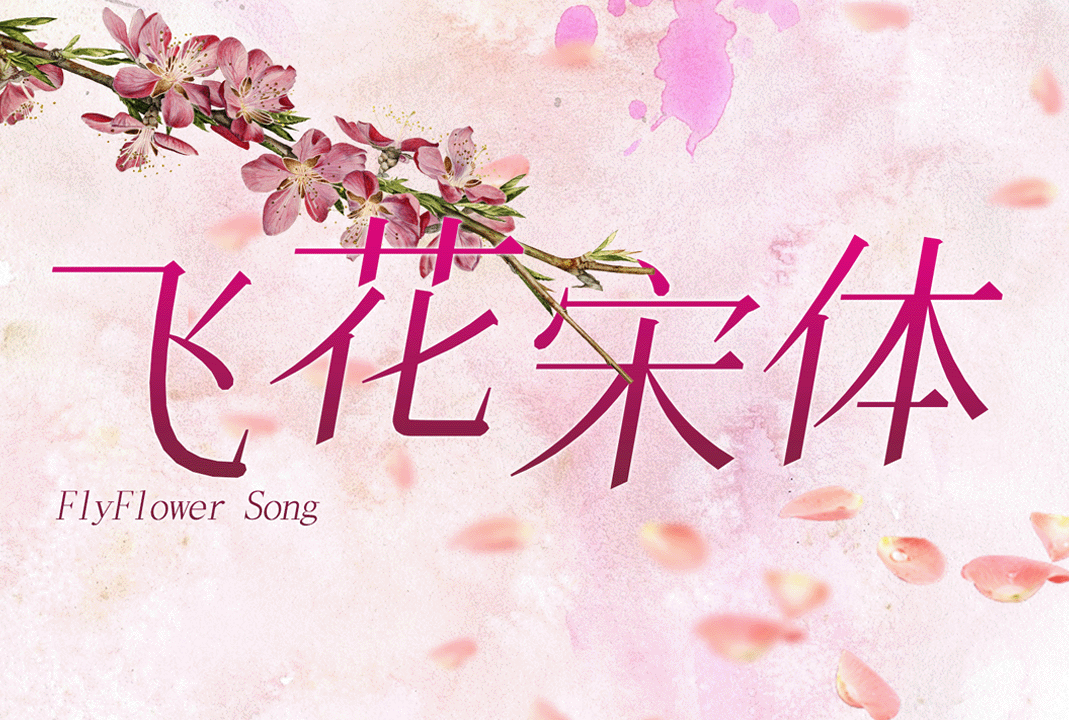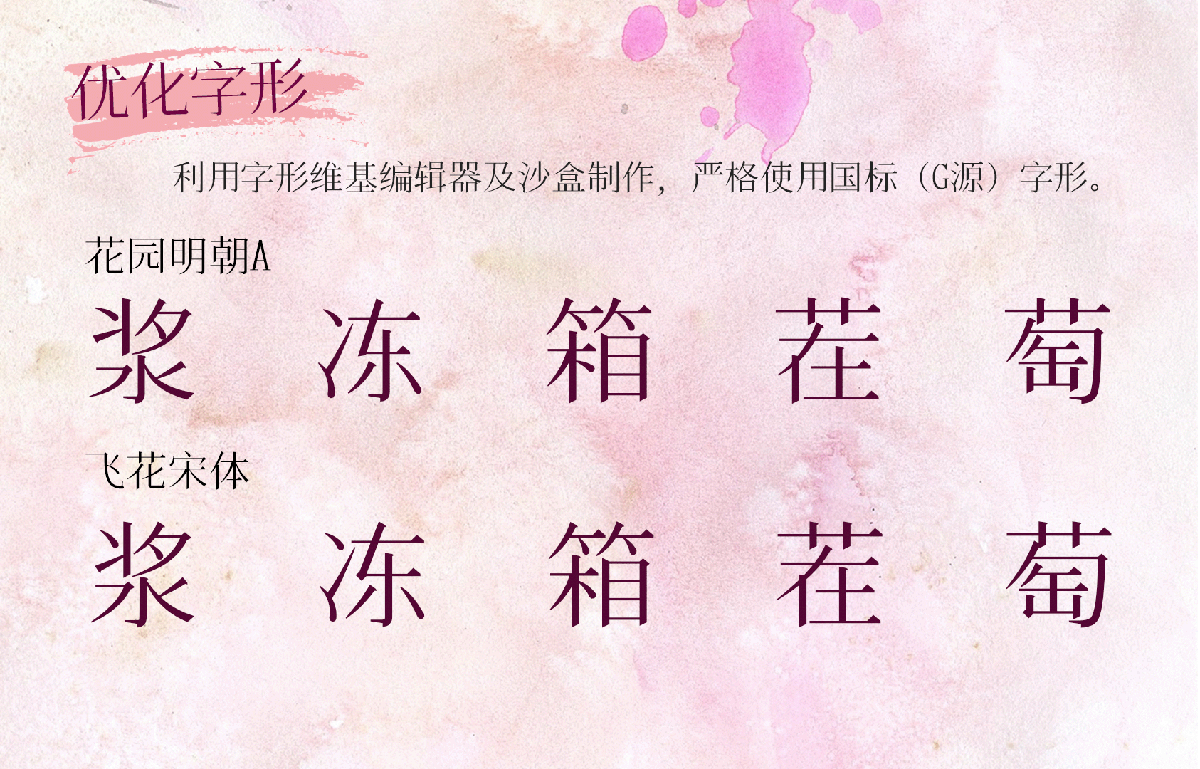
《飞花宋体》是基于花园明朝改造而成的一款适合中文简体实用的宋体字体,英文名为“FlyFlowerSong”。
《飞花宋体》收录汉字数总计超过1万,除了支持简体汉字之外,还支持俄语、希腊语、韩语、拉丁语、盲文以及中学阶段涉及的数学符号,未来如果有可能还会收录少数民族的语言文字。
注意:为了避免文件过大,作者删去了繁体字和一些使用频率极少的符号,如果介意请继续使用花园明朝体。
其他资料:花园明朝是一款免费字体,为GlyphWiki(字形维基)所开发,几乎收录了所有汉字字形。缺点是字形以日本字形为准,有一些字不符合中文书写规范(不论是大陆规范还是港台规范)。